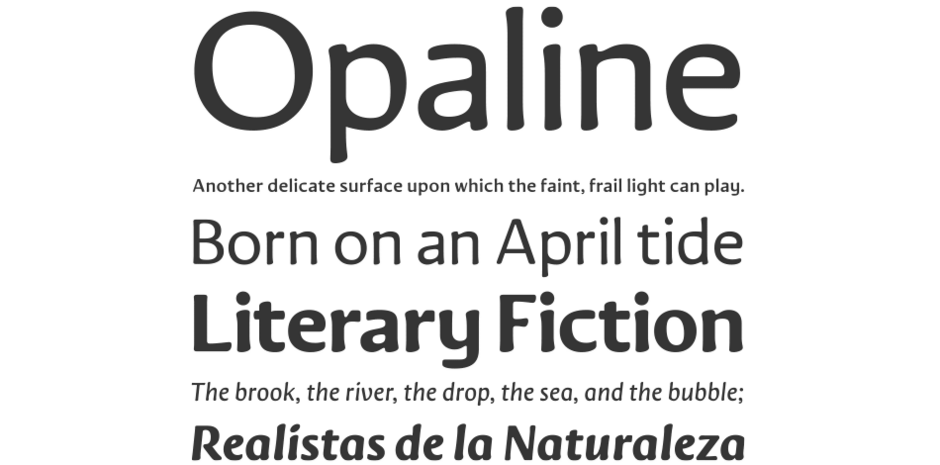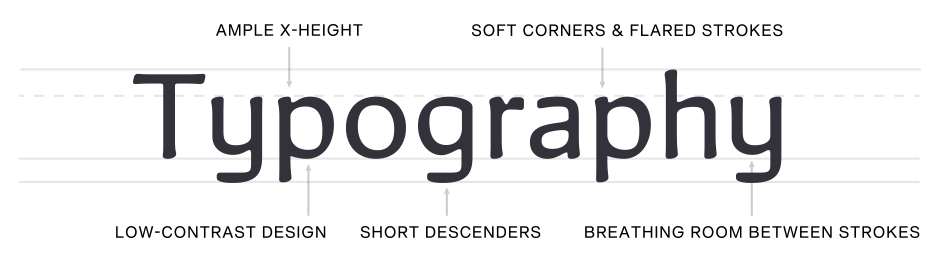
Novaletra Sans CF Fuente Guía de campo
Buenas prácticas
Novaletra Sans CF está construida para sobresalir en tamaños pequeños y medianos, en entornos impresos y digitales. Perfecta para textos, pies de foto, libros y documentos, la elegante construcción de Novaletra ayuda a que el texto fluya y sea fácil de leer, incluso en tamaños muy pequeños. Sus pesos medios son ideales para bloques de texto largos, con pesos más ligeros y más gruesos disponibles para garantizar la máxima versatilidad. La cursiva verdadera, ligeramente condensada y caligráfica, se lee de forma distinta pero relacionada con la romana vertical.
Familia
Ocho pesos de diseños romanos, cada uno con un oblicuo complementario, para un total de 16 estilos.
Fuente Hechos
- Novaletra Sans CF se basó en Novaletra Serif CF y, como ambas comparten un diseño de base, pueden intercambiarse o utilizarse juntas con un mínimo de complicaciones.
- Como su nombre indica, Novaletra se creó con la intención de dar un nuevo enfoque al diseño del cuerpo del texto en formato sans serif.
Raíces
Novaletra Sans CF es un diseño original de Connary Fagen, concebido en 2023 como complemento de Novaletra Serif CF, una fuente con gracias pensada para texto y textos. Los elementos de Novaletra Serif, como sus características de estilo antiguo, se han limado para crear una sin gracias cálida y suave que ofrece una legibilidad maravillosa que no suele encontrarse en los tipos de letra sin gracias. Los sutiles toques caligráficos y las esquinas suaves aportan interés visual, mientras que la construcción sencilla y la altura x media maximizan la legibilidad en tamaños pequeños.
Legibilidad
Novaletra Sans CF se ha diseñado expresamente para su uso en texto, y se lee bien en tamaños pequeños y medianos. Aunque llena de carácter y calidez, Novaletra nunca sacrifica la legibilidad. Su diseño de bajo contraste garantiza una lectura fácil.
Cómo detectar Novaletra Sans CF
Opciones alternativas
Maridaje perfecto